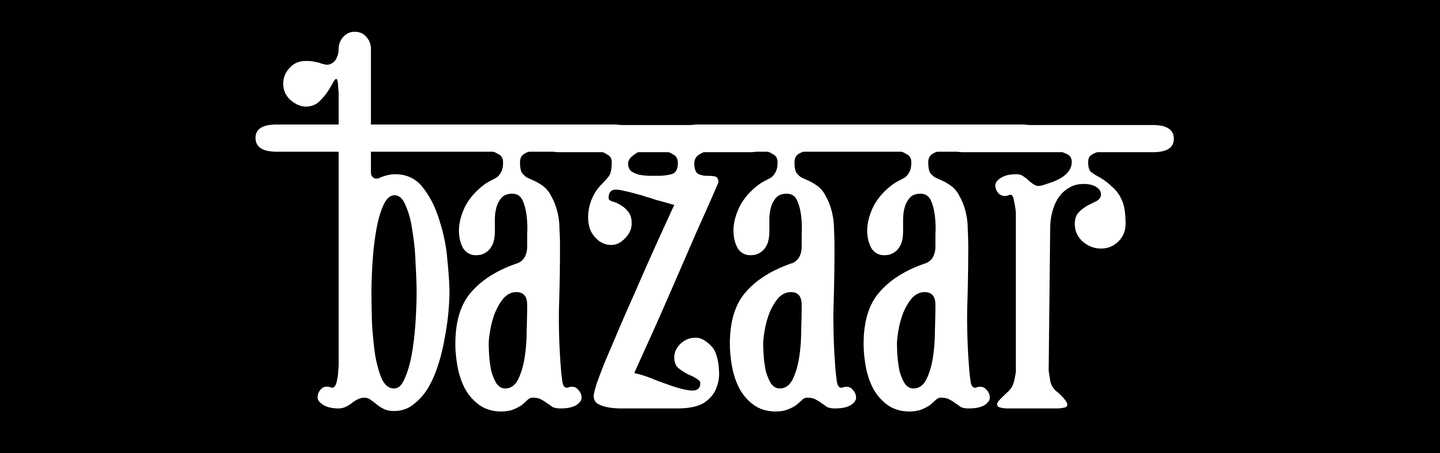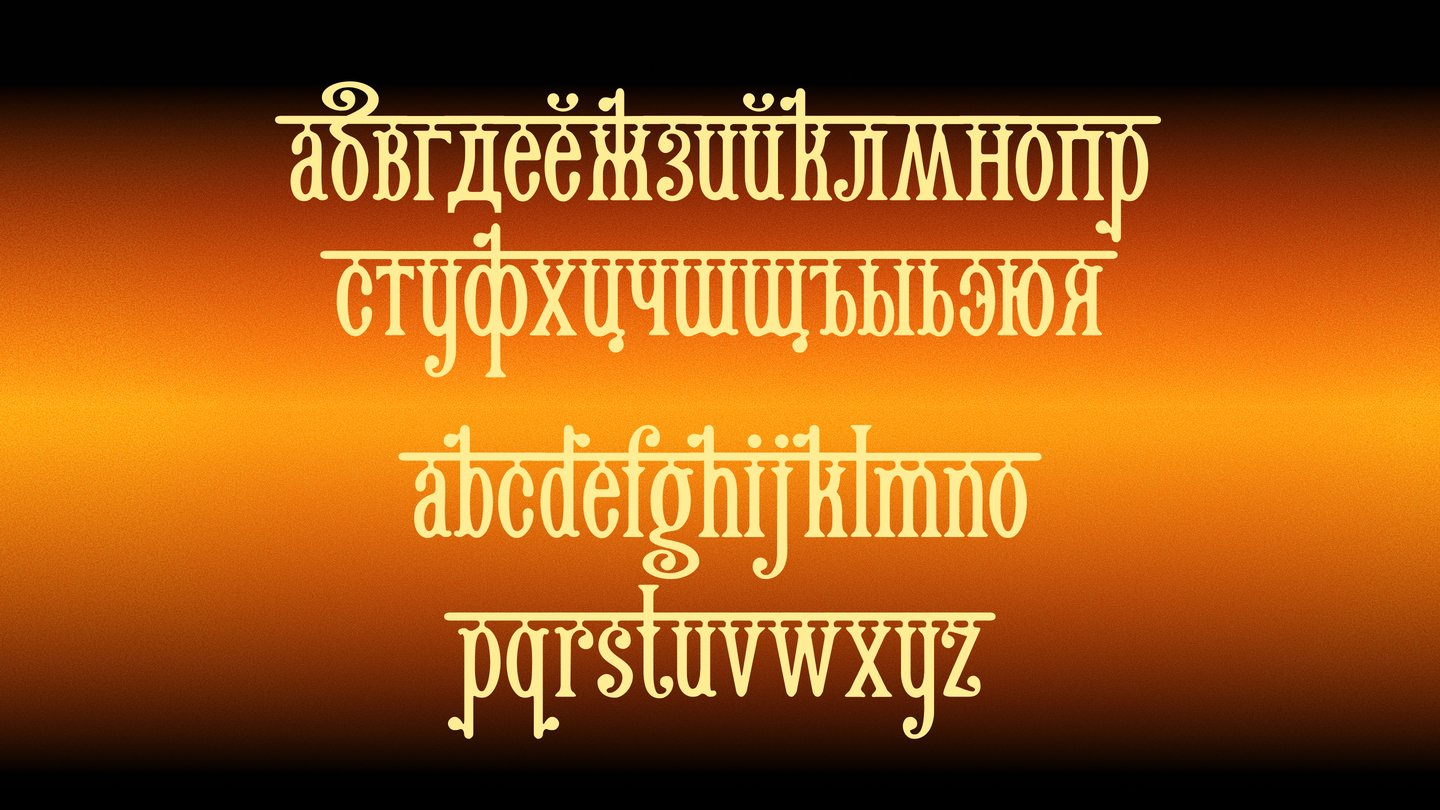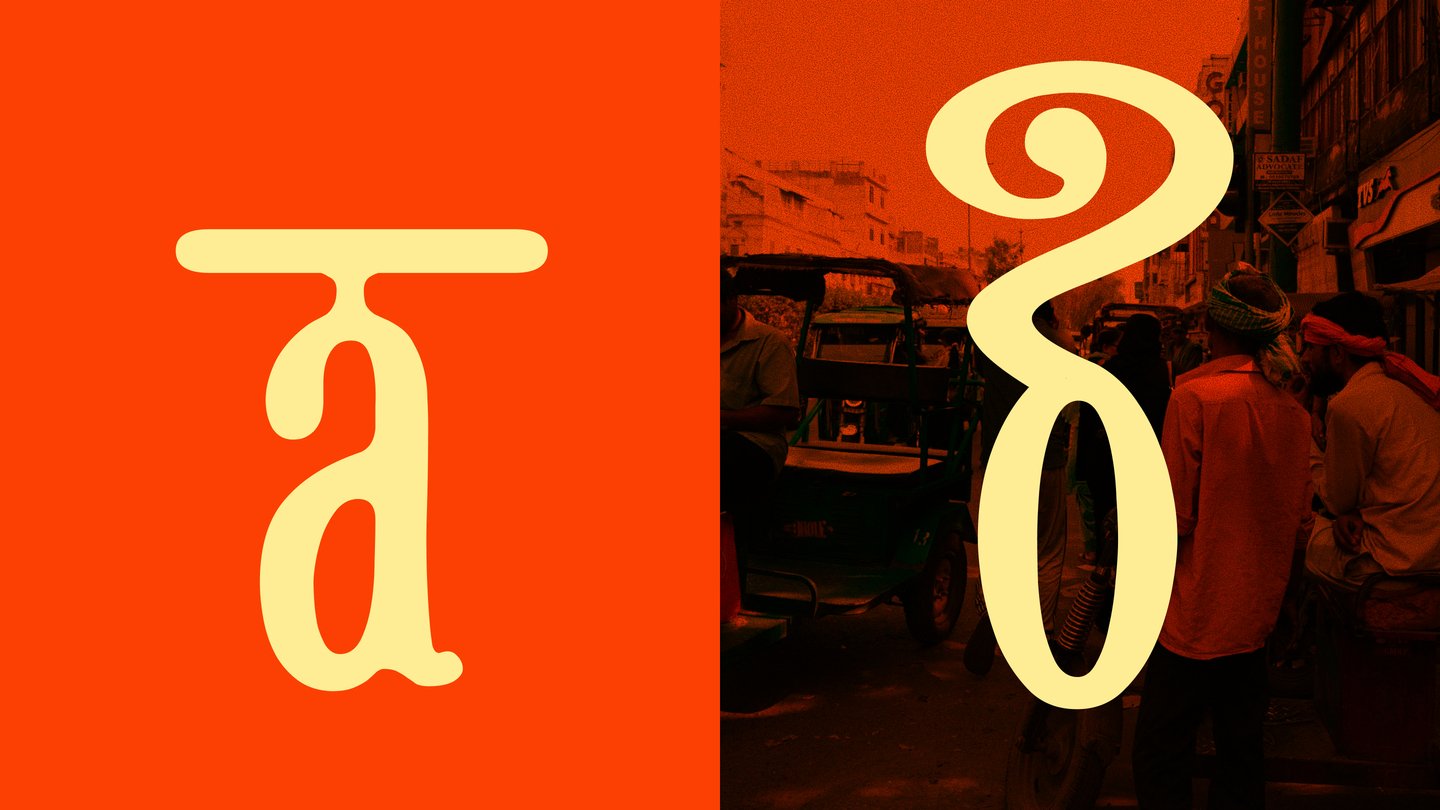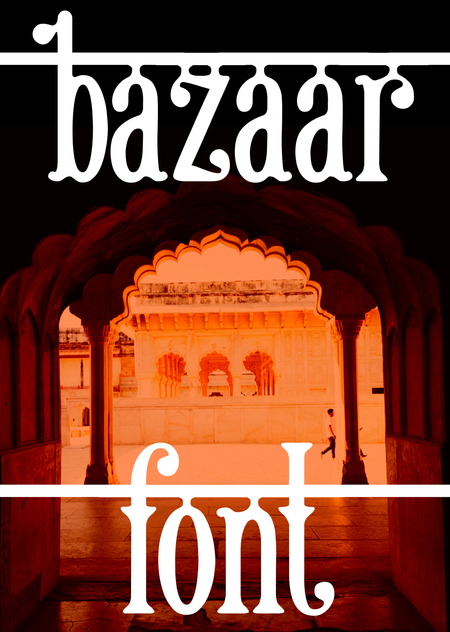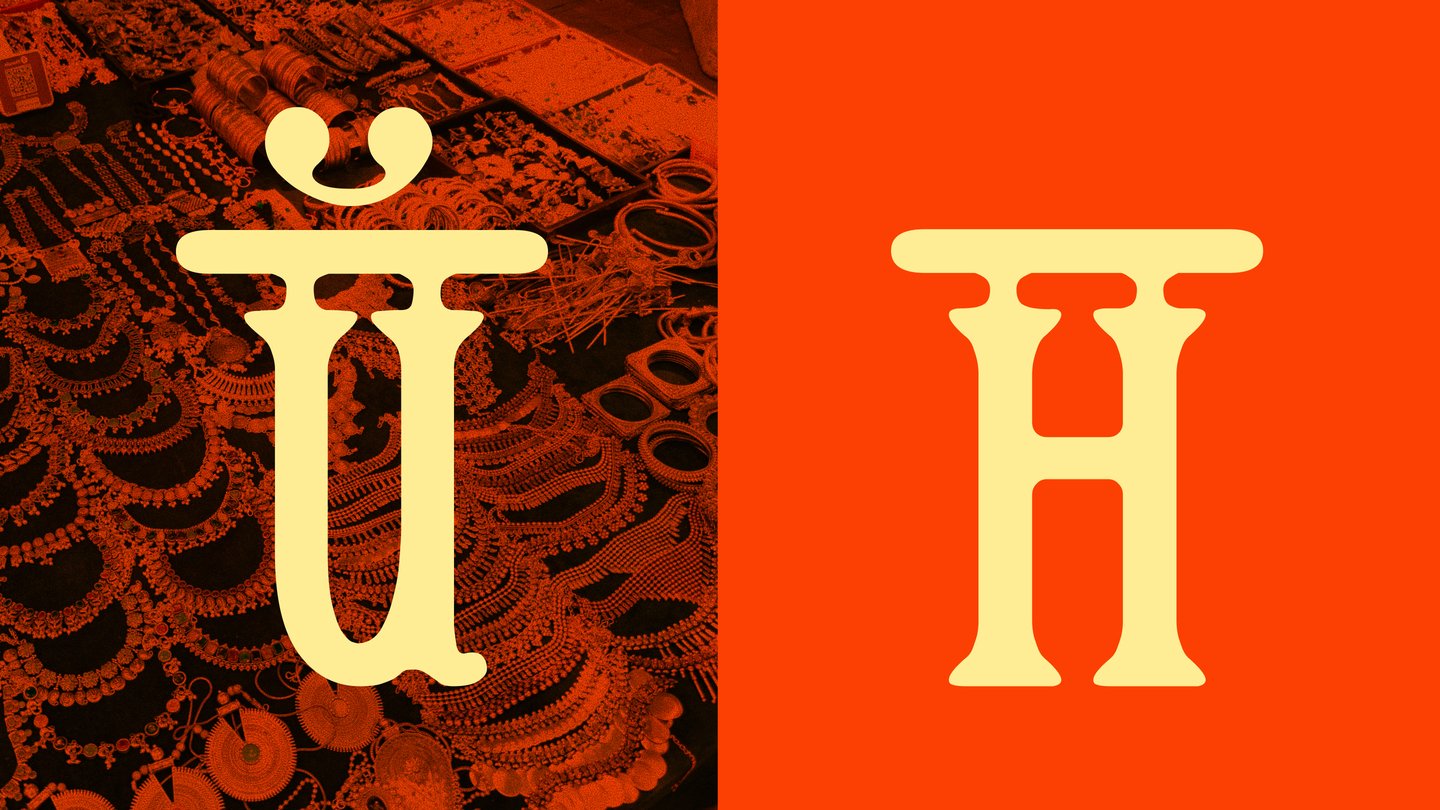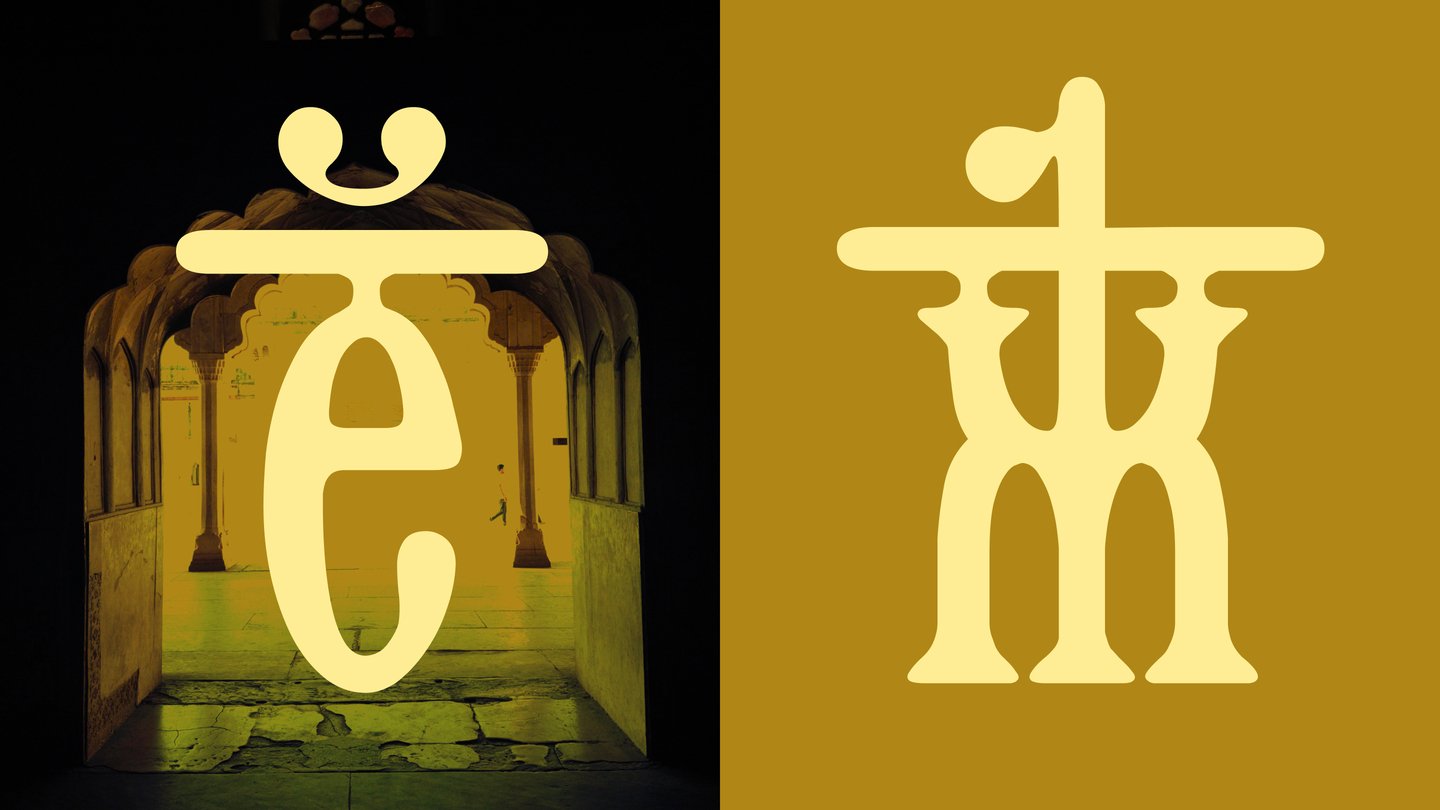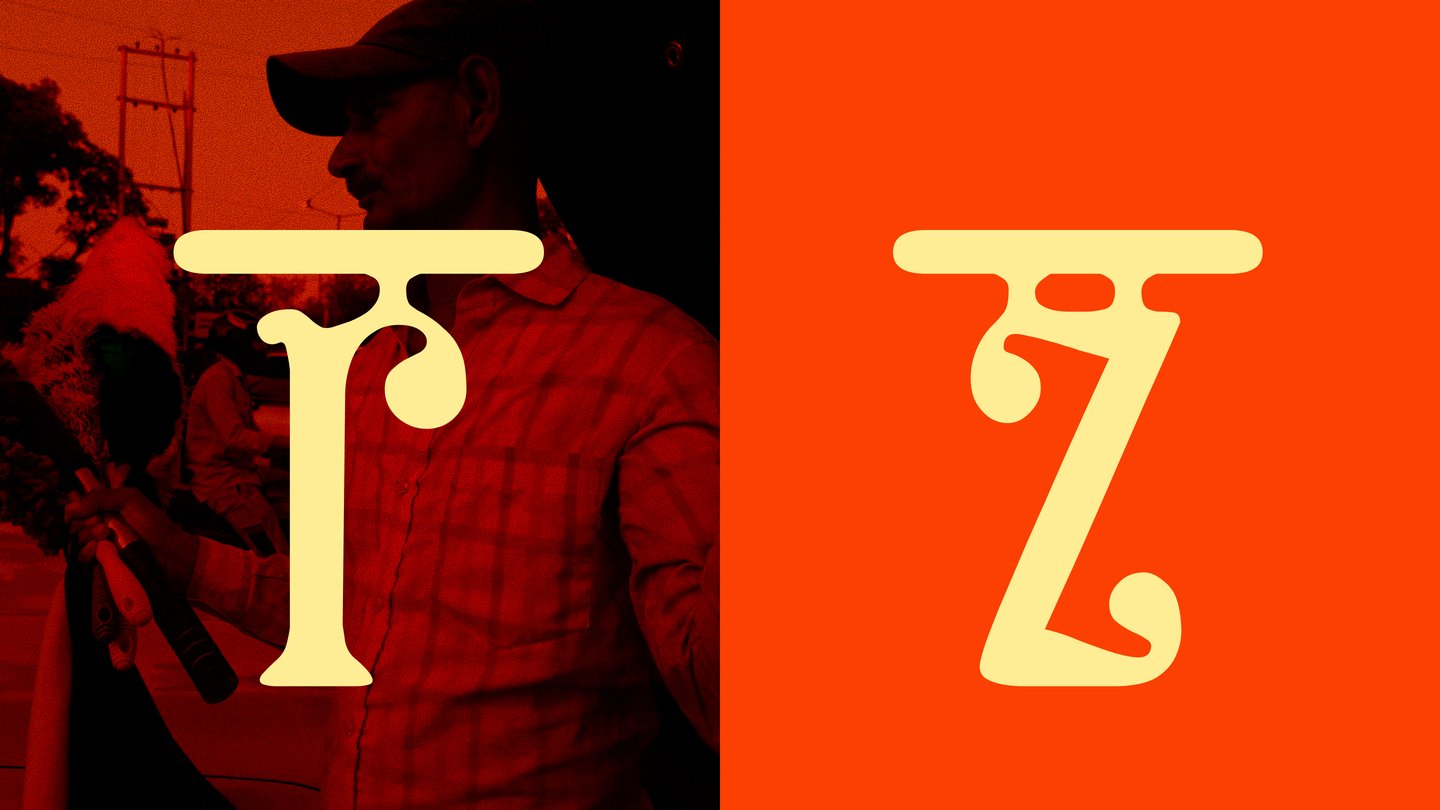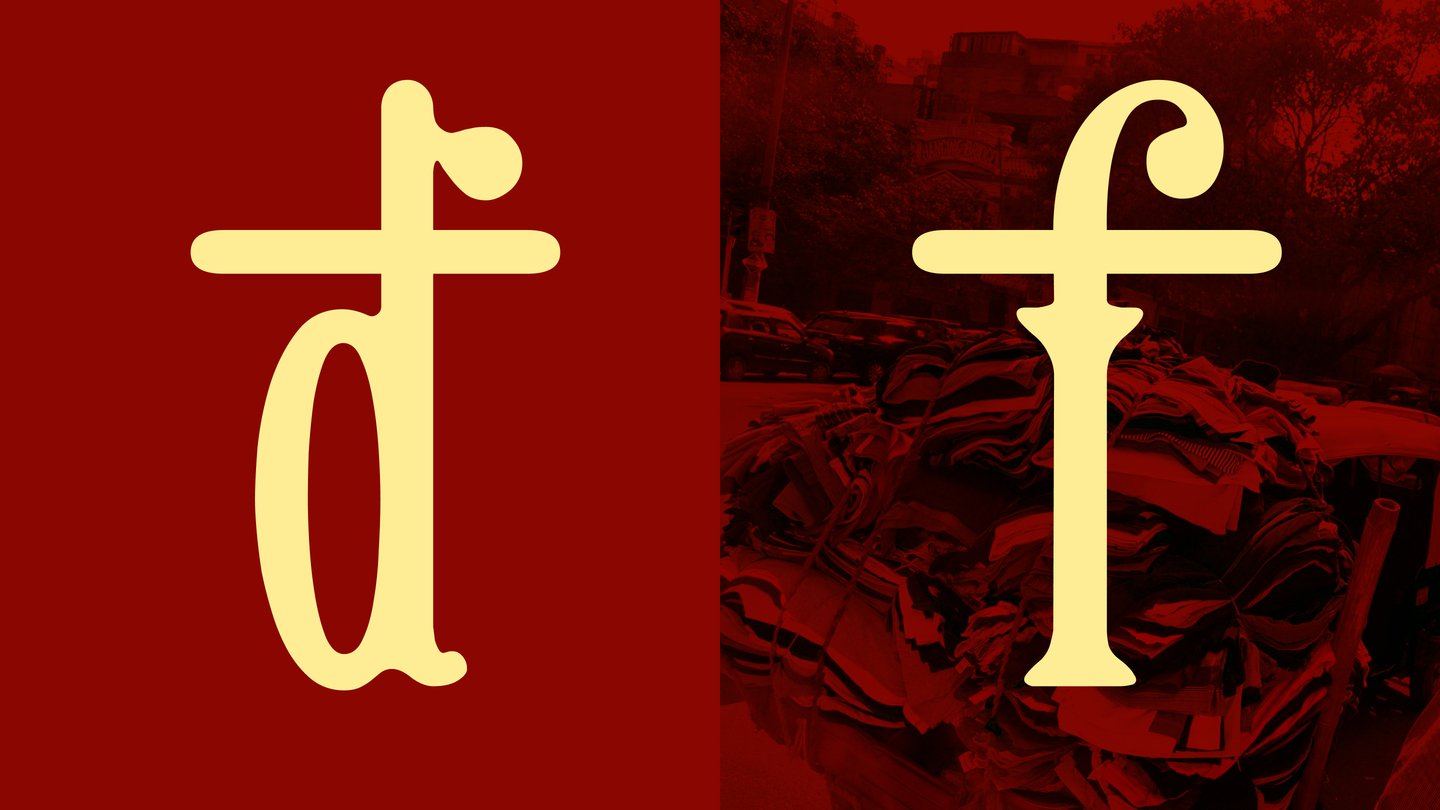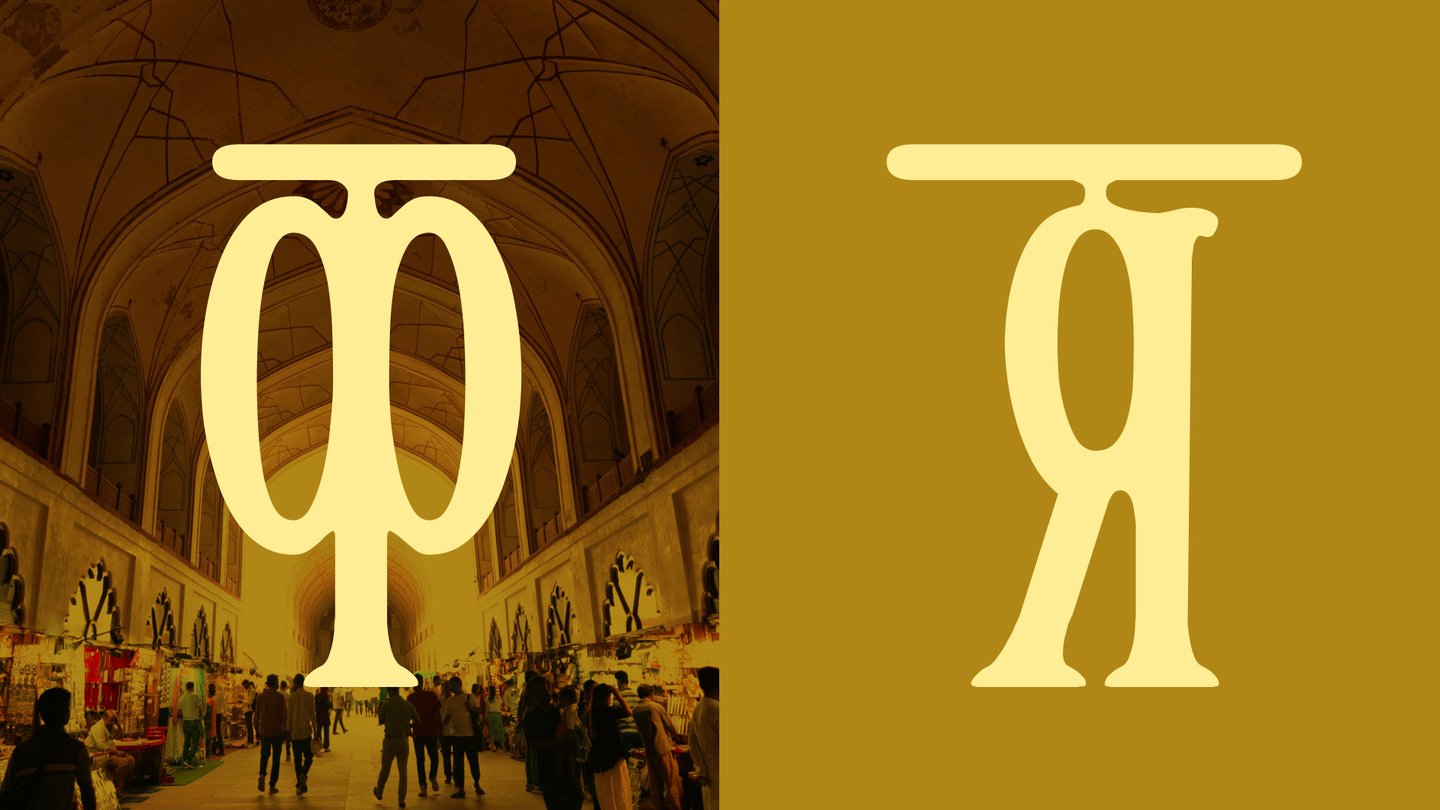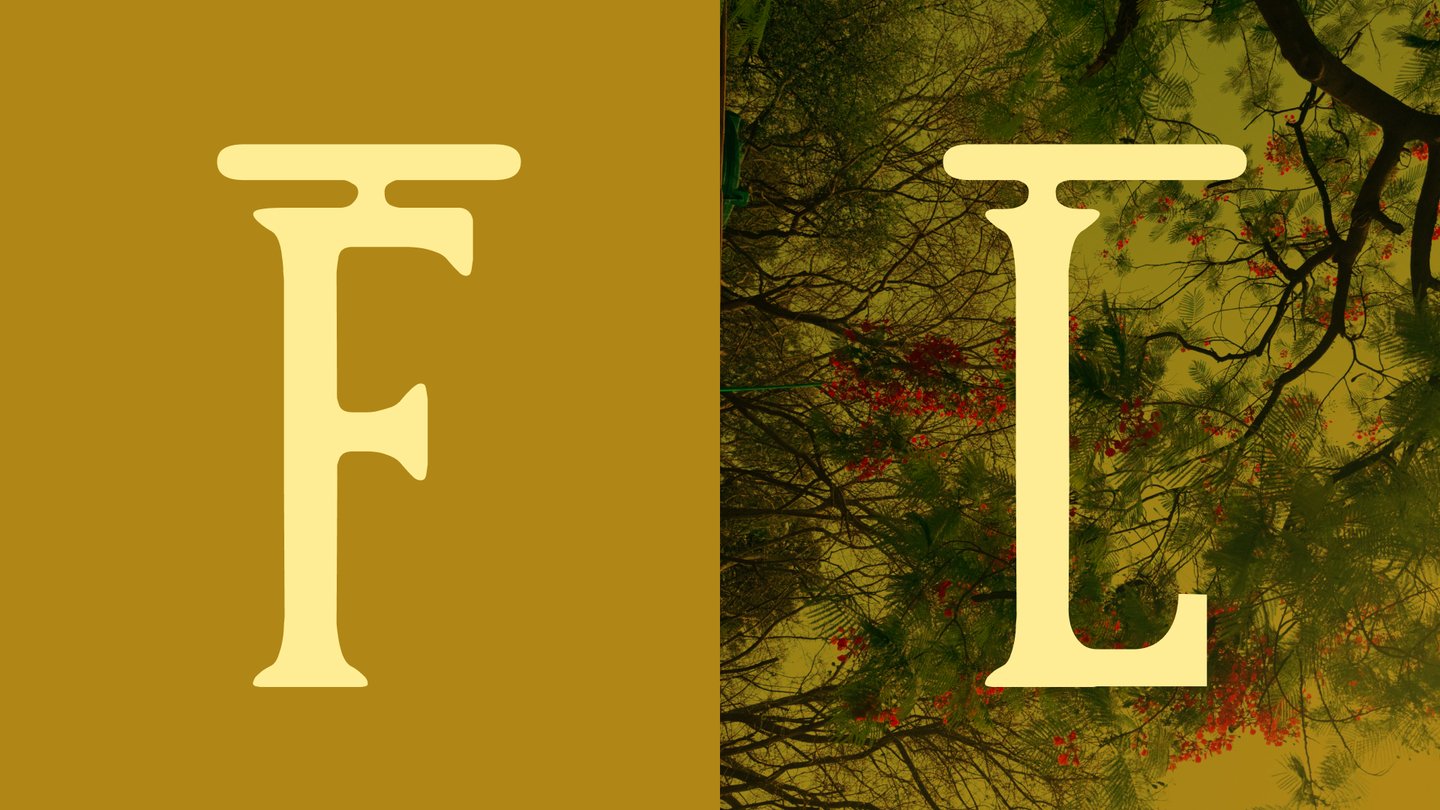
Bazaar — шрифт, вдохновлённый уличной типографикой и рынками Дели. Буквы словно подвешены на базарные нити, а проходящая сквозь них горизонталь превращает строку в метафору путешествия по Индии — шумного, насыщенного и непрерывного
Bazaar — это рынок индийских специй в холодном Санкт-Петербурге. В основе айдентики шрифт Bazaar и градиенты, символизирующие остроту специй.